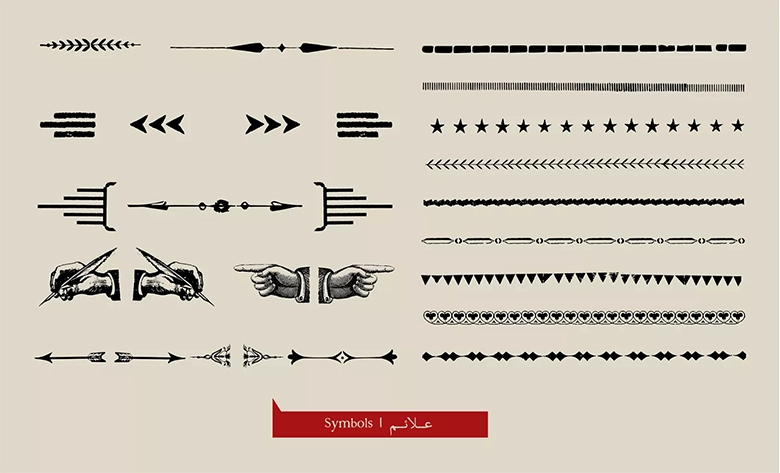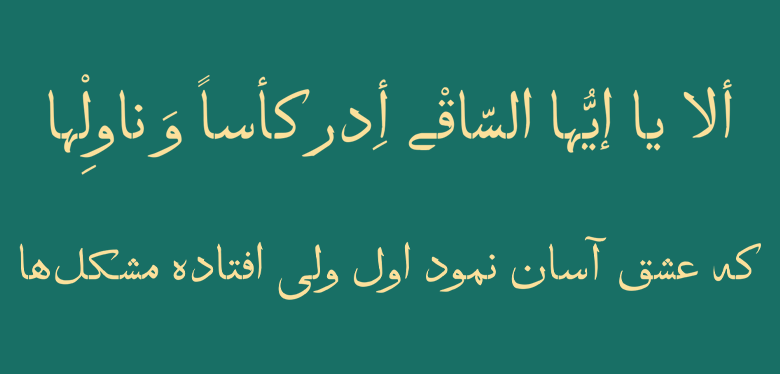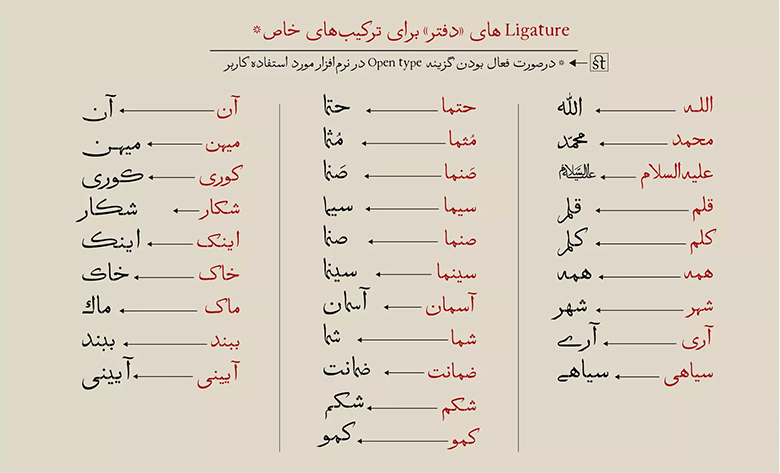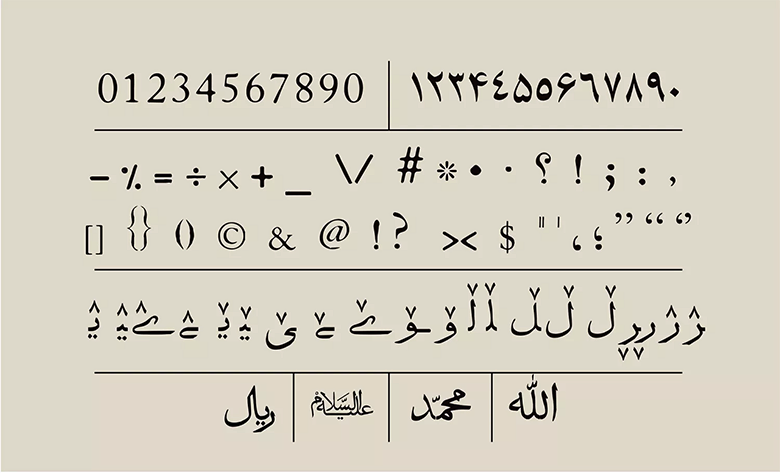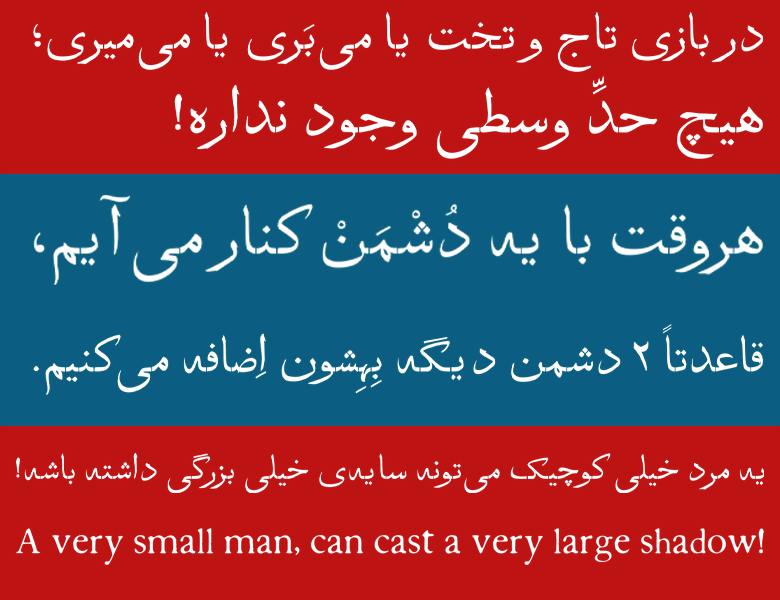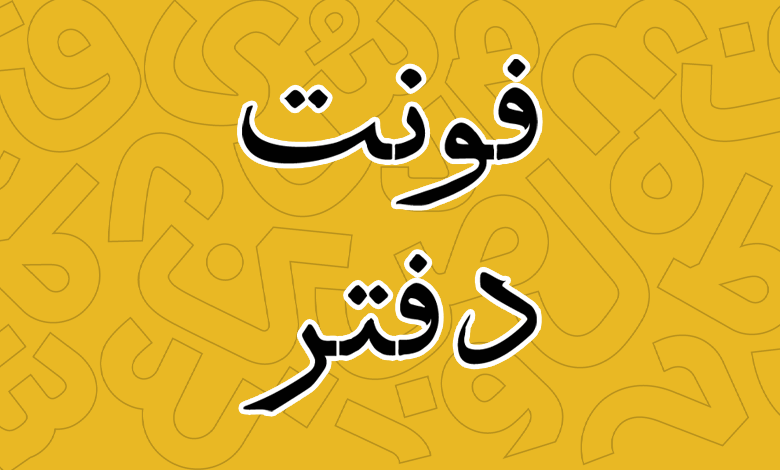
فونت دفتر (Daftar)
فونت دفتر (به انگلیسی: Daftar) در گروه فونتهای مناسب مطبوعات قرار میگیرد که بر اساس خط نسخ طراحی شده و میتوان از آن در مواردی همچون تیتر، عناوین، تبلیغات و بهطور کلی کارهای گرافیکی که جنبه انتقال حس نوستالژی را دارند استفاده کرد. فونت دفتر رایگان نبوده و در یک نسخه Regular قابل خریداری است.
فونت دفتر در استودیویی با همین نام توسط رضا سالاری فر طراحی شده است با جمعآوری نسخههای چاپی و اسناد بهجا مانده از آن دوران این فونت را بازسازی کرده و در قالب فونت مورد استفاده در کامپیوتر تبدیل کرده است.
در ادامه این نوشته از سایت فونتچی به نقد و بررسی کاملی از امکانات و قابلیتهای بهخصوصی که قلم دفتر دارد خواهیم پرداخت که میتوانید از این فونت در کارهای گرافیکی که نشان دهنده حس قدیمی بودن، اصالت داشتن و ساختار نوستالژیک تا قبل از دهه ۵۰ را دارند استفاده کنید.
قبل از هرچیزی لازم به ذکر است که، برای ایجاد حس و حال کهنه و نوستالژیک، فونت دفتر برخلاف نسخههای چاپی الهام گرفته شده از آن، دارای کمی خوردگی، بی نظمی در اتصال حروف و عدم تناسبات، آن هم بهطور عمدی است.
بنابراین اگرچه این حروف در زمان خود ویژه اعلانهای رسمی بوده است اما اکنون یک فونت نمایشی محسوب میشود و بیشتر مناسب آثار گرافیکی با حال و هوای قدیمی (نوستالژیک) است.
سبک طراحی و وزن فونت دفتر
سبک طراحی قلم دفتر بر اساس خط نسخ صورت گرفته شده است. این فونت دارای خطوط کرسی و منحنیهای نرم و دوست داشتنی است. ضخامت فونت در سرتاسر حروف یکسان نبوده و در دندانهها و زوایا از آنها کاسته میشود. همچنین حروف به هم چسبیده نبوده و گویی که با استفاده از ماشینهای چاپ قدیمی روی کاغذ چاپ شده باشد دارای فاصلهای جزئی از هم هستند که همان حس و حال قدیمی صنعت چاپ را منتقل میکند.
فونت گرامافون که یکی دیگر از قلمهای ساخته شده بر اساس خط نسخ است نیز از همین ساختار فاصلهدار حروف ایجاد شده است که طراحی نزدیکی هم به این قلم دارد.
در بسته دانلود فونت دفتر فقط با یک وزن Regular مواجه هستیم که این وزن کاملا برای استفاده در عناوین و حتی متون طولانی مناسب به نظر میرسد. اگر چه بیشترین کاربرد فونت دفتر برای اندازههای بزرگ است، اما این فونت در حد فاصل اندازههای ریز تا ترکیبات درشت، همچنان زیبایی و خوانایی خود را حفظ میکند؛ چرا که دارای حروف و ترکیبات جایگزین متنوعی هم هست.
پشتیبانی از علائم و اشکال کمکی
خاصترین ویژگی دفتر امکان استفاده از علائم و اشکال کمکی است که در همان سالها نیز از این ساختار قلم در نسخههای چاپی استفاده میشده است. این علائم که در تصویر زیر آنها را مشاهده میکنید، در بخشهای مختلفی از نوشته با هدف جداسازی و تزئین استفاده میشد که حتی در اسناد رسمی هم رواج داشته است.
پشتیبانی کامل از ۴ زبان مختلف
فونت فارسی دفتر محدود به این زبان نیست و از سایر زبانهای خاورمیانهای و لاتین نیز پشتیبانی کاملی همراه با حروف، اعداد، سمبلها و کاراکترهای تزئینی را دارد. این زبانها شامل عربی، انگلیسی و کردی هستند.
همانطور که در تصویر فوق مشاهده میکنید، در بخش اعراب شاهد همنشینی درستی هستیم که با قرار گیری اعراب اصلی در کنار کاراکترهایی همچون «تشدید، سکون و همزه» فاصله اعراب بههم ریخته نمیشود.
در فونت daftar انگلیسی از طراحی اختصاصی استفاده نشده و از فونتهای اپن سورس که ساختاری نزدیک به این فونت دارند استفاده شده است. اما با این تفاوت که کمی در آن دست برده شده و خوردگیهایی در بافت حروف ایجاد شده تا کاملا ساختاری هماهنگ با نسخه فارسی داشته باشد.
دارای حروف و ترکیبات جایگزین متنوع
فونت دفتر یکی دیگر از فونتهایی است که سرشار از ترکیبات اختیاری است. با استفاده از حروف جایگزین در فونت دفتر که از طریق تنظیمات Open Type نرمافزار قابل استفاده هستند، میتوانید حروف تکی یا ترکیبات دوتایی از حروف را در ابتدا، میانه یا انتهای کلمات با ظاهری متفاوت و در چند شکل مختلف تایپ کنید.
این ترکیبات اختیاری از دو جهت در طراحی متونی که نیاز به حس و حال نوستالژیک یا تبلیغاتی دارند حائز اهمیت است. اول اینکه موجب ایجاد تناقضاتی در برخی کلمات خواهد شد که دارای طراحی حروف متفاوتتری نسبت به سایر کلمات هستند. در نتیجه در متون بلند به خوانایی کمک خواهد کرد. دوما اینکه استفاده از این ترکیبات در کارهای تبلیغاتی برای کلماتی که تاکیدی بوده و باید بیشتر مورد توجه قرار گیرد، موجب جلب توجه بیشتر مخاطب میشود. در تصویر زیر نمونههایی از آنها را میبینید.
این ترکیبات محدود به تصویر بالا نبوده و شامل حروف و ترکیبات مختلفی هستند که جدای از ظاهر متفاوت، در برخی ساختارها کلمات را درشتتر از آنچه در ترکیبات عادی هستند نشان خواهند داد. از همین جهت هم به خوانایی نوشته، هم زیبایی و هم جلب توجه بیشتر کاربر تاثیر خواهد گذاشت.